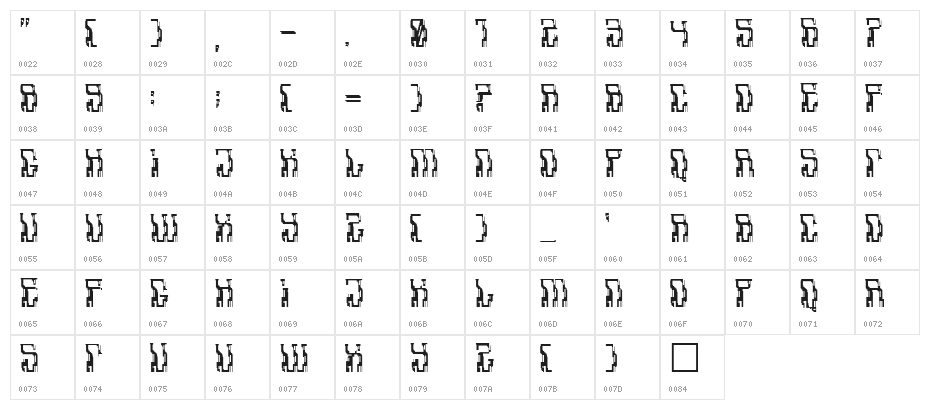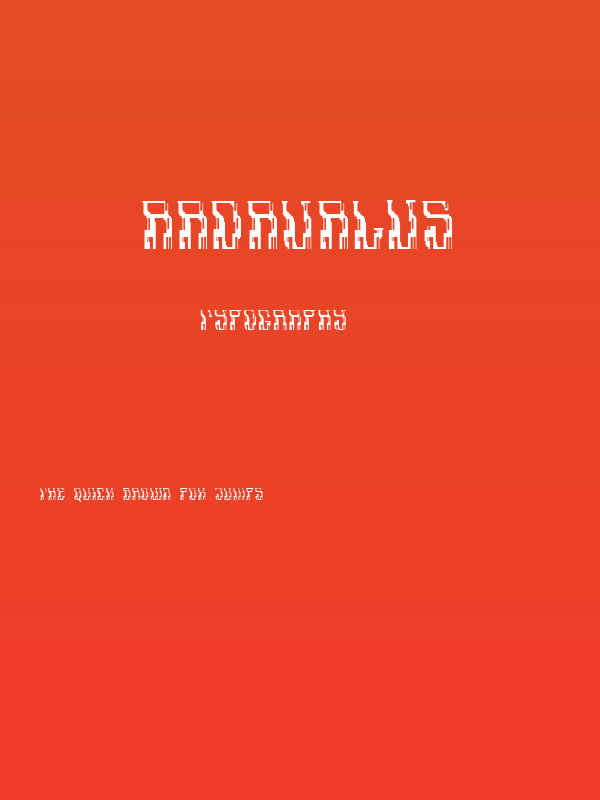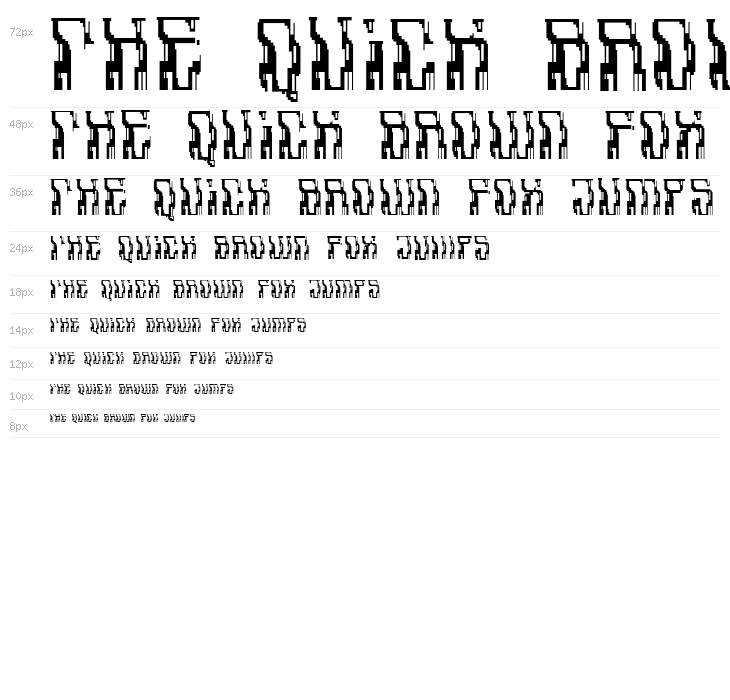
Aadavalus Font
| Estilo general | Futuristic, Digital |
| Caso de uso | Logos, Headlines, Posters |
| Proyectos propuestos | Ideal for sci-fi themed designs, digital art projects, video game graphics, and tech-related branding. |